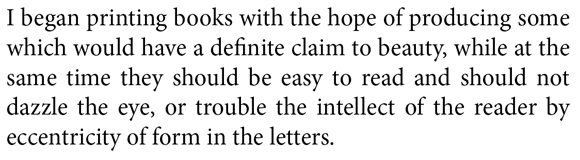
Cuando componemos un texto sin ninguna otra pretensión que transmitir una información al lector, debemos cuidar su «color tipográfico». Creo que la mejor definición de este concepto es la que hace el tipógrafo José María Cerezo: “El color tipográfico se define como el tono gris global de un escrito bien resuelto, y este se obtiene cuando la textura de la composición es uniforme, sin calles, blancos excesivos, líneas apretadas o sueltas”.
De todas las formas en las que podemos componer un texto, en bandera, centrado o justificado, es en esta última donde podemos encontrarnos de manera más evidente, con problemas en el tono del texto. En una composición en bandera todo el espacio sobrante se acumula en los finales de línea y, como estos son irregulares el espacio entre las palabras se mantiene constante. Lo que redunda en un color tipográfico homogéneo. El gran Eric Gill defendía esta manera de componer los textos y lo llevó a la práctica en su libro “An essay on typography” (1931).
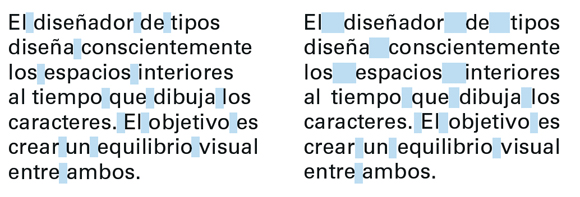
Sin embargo en una composición justificada, la necesidad de igualar la longitud de las líneas hace que los espacios entre las palabras (o entre las letras) tengan que ser irregulares para lograr este fin. Y es aquí donde el temido problema de una composición con un mal “color tipográfico” puede aparecer, máxime si la medida de la línea es pequeña y el tamaño de la tipografía escogida grande para la misma.
Fijaos en la composición inferior, me imagino que muchos de vosotros os estaréis echando las manos a la cabeza. Sobre todos los más sensibilizados con los espacios microtipográficos.
Las primeras tres líneas muestran unos espacios excesivos entre palabras. En comparación la cuarta y la quinta aparecen “apretadas” y luego las tres últimas se vuelven a “abrir”. En definitiva un perfecto ejemplo de una composición irregular que ofrece unos espacios excesivos.
¿Un truco? Poned el texto “boca abajo” y veréis como esos espacios se hacen más evidente.
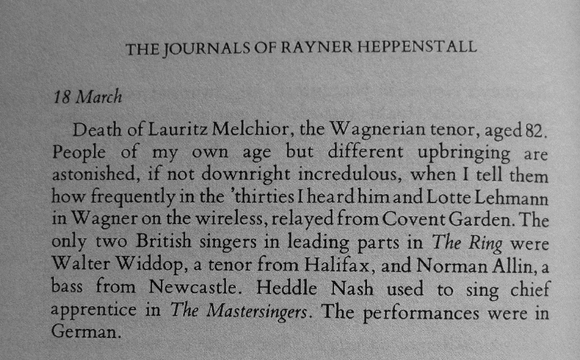
Y sobre esto me gustaría hablar hoy. Ya sabéis que para igualar la medida de las líneas podemos actuar sobre los siguientes parámetros: espacio entre letras, espacio entre palabras, partición de palabras y escala del tipo. Dejando al lado esta última opción, no me voy a poner integrista y expulsar del paraíso de los tipógrafos a los que la utilicen (eso sí, con mucha moderación), vamos a hablar de las diferentes posturas por las que podemos optar a la hora de utilizar las opciones disponibles en el programa informático más popular de composición de páginas, Indesign.
Indesign, tienen respuesta para este problema, por medio de los estilos de párrafo que podemos crear y que se engloban en las “misteriosas” P&J (Partición y justificación, para el que le haya sonado raro).
Por medio de estas opciones podemos indicar los porcentajes relativos a los espacios entre letras y palabras, la escala del glifo y la manera en la que se van a partir las palabras, en el caso de que sea necesario.
No es el objetivo de este artículo meterse a fondo con el tema de la configuración de las P&J, ya lo haremos en otro dedicado en exclusiva a este tema. Prefiero que a raíz de la lectura de este artículo tengamos una posición clara respecto a la importancia del espacio regular entre palabras en la composición tipográfica con respecto a un parámetro del programa. Así que, por ahora, vamos a fijarnos en como partimos las palabras, que opciones nos ofrece Indesign y los “peligros” que corremos si no tenemos claro lo que hacemos.
Antes de continuar me gustaría hablaros de un personaje importante de la historia de la tipografía: Ruari McLean. McLean (1917-2006), fue un gran tipógrafo inglés, trabajó para Penguin, él fue el responsable de proponer a Jan Tschichold para trabajar en la firma, profesor de tipografía en el Royal College of Art, editor de la revista Motif y autor de numerosas obras sobre tipografía como el Thames&Hudson Manual of Typography, How Typography Happens, publicado por la British Library, o Modern Book Design.
En mi biblioteca yo tengo un libro editado por él Typographers on type que es una maravillosa selección de textos escritos por tipógrafos sobre su oficio.
Este santo varón dejó escrita una consideración lapidaría: La del espacio cerrado entre palabras (el mínimo necesario para distinguirlas) como el “principio absoluto” de toda buena composición tipográfica.
Así que tenemos nuestra flamante herramienta informática y un poderoso concepto donde agarrarnos. En lo referente al tema que nos ocupa, lo que más nos llama la atención es el selector que aparece en el cuadro de opciones de separación por sílabas: Si deslizamos el separador hacía “Espaciado óptimo” tendremos más guiones y viceversa… ¿qué elegimos?
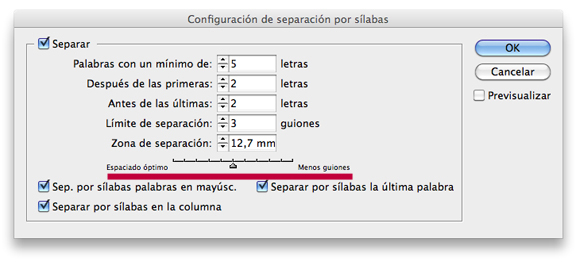
¿Qué pensamos que es más correcto, evitar guiones o conservar un espacio cerrado?
Y esta es nuestra posición: Mirad, evitar en lo posible la aparición de varías líneas consecutivas acabadas con guiones es una aceptable “norma” de composición, pero esta no debe aplicarse nunca sacrificando el correcto espacio entre palabras. Y sobre el “correcto espacio entre palabras” en una composición, yo creo que hay unanimidad entre los tipógrafos incluso entre figuras al principio tan distantes entre si como William Morris y Jan Tschichold:
Además, siempre podemos sacar fuera de la caja de texto los guiones y signos de puntuación si nos sentimos «morir» al ver un par de guiones consecutivos, de esta manera se disimulan un poco. Esto antes de tocar «el principio absoluto». ¡¡Hacedlo por Ruari!!